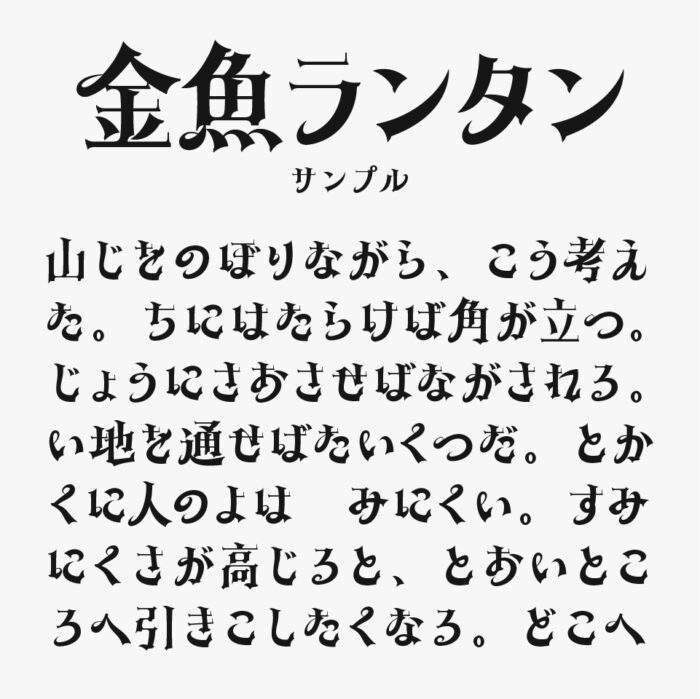
金魚ランタン
金魚ランタンフォントは、筆の勢いを感じさせつつもどこかレトロな遊び心を残したデザインフォントです。
文字ごとの抑揚やハネ、払いにこだわりがあり、古典的の風格と可愛らしさの両方の良いところが詰まっているデザインなフォントです。
日本語版のブラックレター体のような雰囲気があるファンタジー感がとってもステキなフォントです。
金魚ランタン